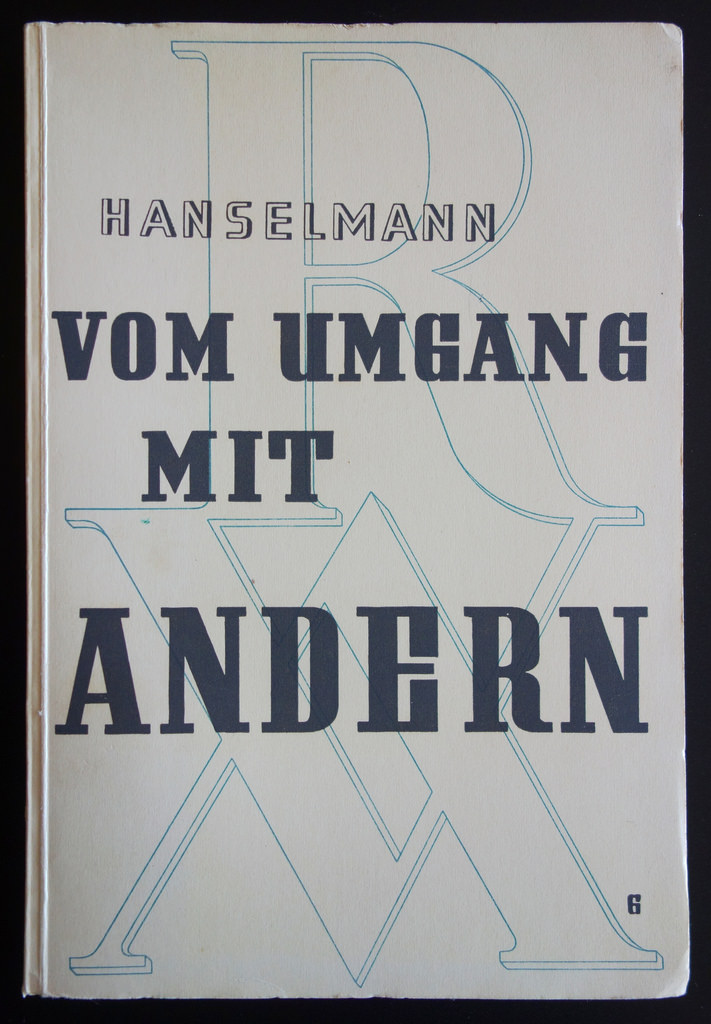
Druckschrift auf Buchcover um 1930
Kann mir jemand weiterhelfen bei der Identifikation der Schriften auf diesem Buchcover? (Heinrich Hanselmann: Vom Umgang mit Anderen, Zürich: Rotapfel-Verlag, 1931.) Die Titelschrift kam bei einer Reihe von Titeln des Autors zum Einsatz.
Heinrich Hanselmann: Vom Umgang mit Anderen, Zürich: Rotapfel-Verlag, 1931.
Das ist vmit sehr großer Wahrscheinlichkeit damals keine Satzschrift gewesen, sondern eine Arbeit eines Grafikers, der diese Buchstaben gezeichnet hat.
Ein deutliches Indiz hierfür: Identische Buchstaben, also die 3 M oder die 2 G sind nicht deckungsgleich. Achte hier auf die untere Punze im M, da ist beim ersten M die rechte Spitze etwas höher, während dies beim 2. m die linke ist. Beim G fällt das 2. etwas breiter aus, und auch dere Spalt ist etwas weiter. Daher eine gute Chance, dass diese Schrift weder in Blei veröffentlicht noch digitalisiert wurde. - zumindest noch... :-)